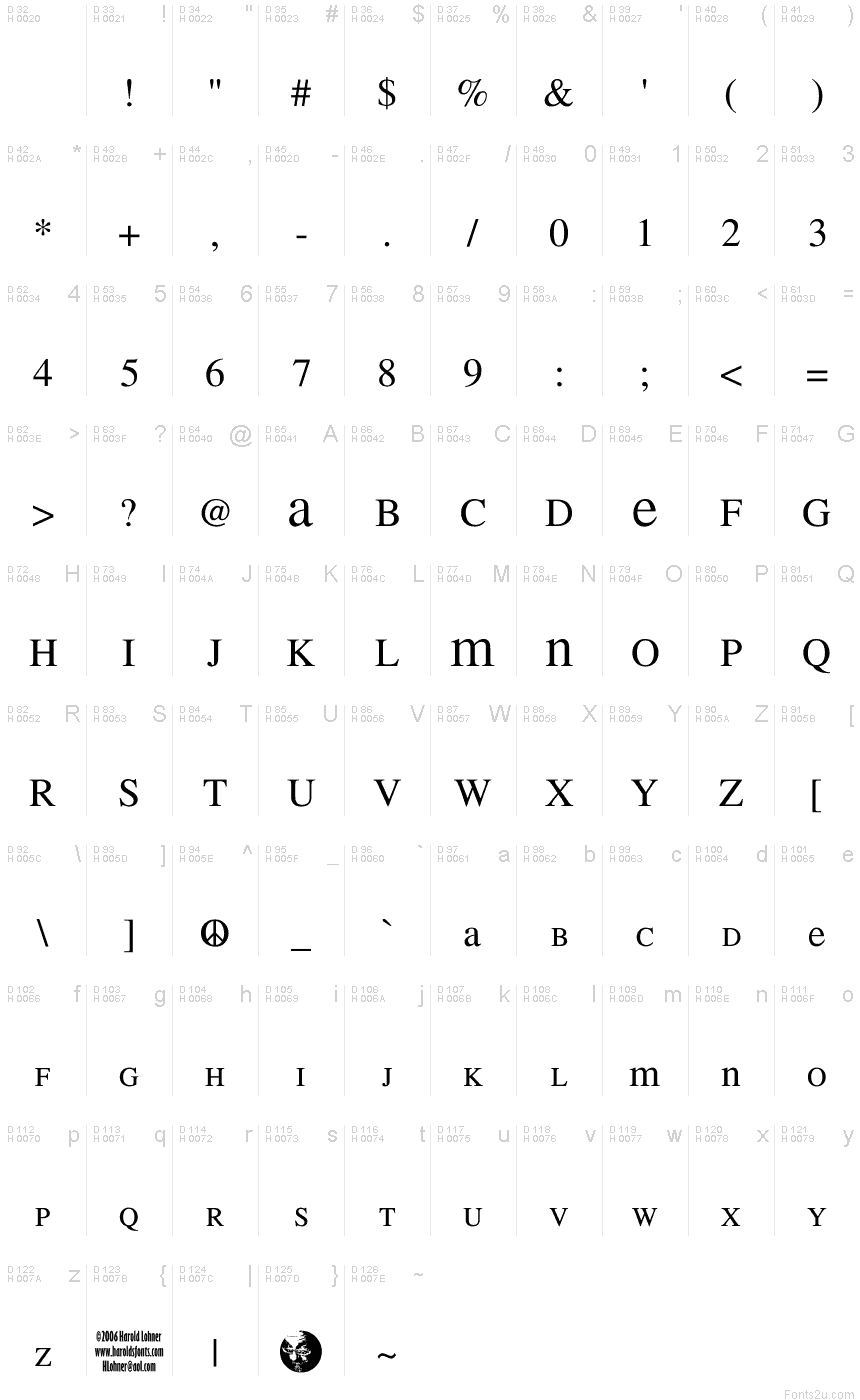
MEAN 26 Serif
MEAN 26 Serif autorstwa Harolda Lohnera to darmowy krój szeryfowy o długich, smukłych krzywiznach i wyraźnych, wspartych szeryfach. Charakteryzuje się wyrafinowanym, redakcyjnym rytmem, wąskimi literami, otwartymi łukami oraz wyraźnym kontrastem między prostymi pociągnięciami a bardziej miękkimi, zaokrąglonymi kształtami.
MEAN 26 Serif świetnie sprawdza się w tytułach magazynów, na plakatach, okładkach książek, w zaproszeniach oraz w projektach identyfikacji wizualnej, które wymagają formalnego, literackiego sznytu. Ten darmowy font pasuje również do logotypów i krótkich haseł, ponieważ wydłużone kształty i ostre szeryfy nadają krótkim blokom tekstu wyrazisty, dopracowany charakter.